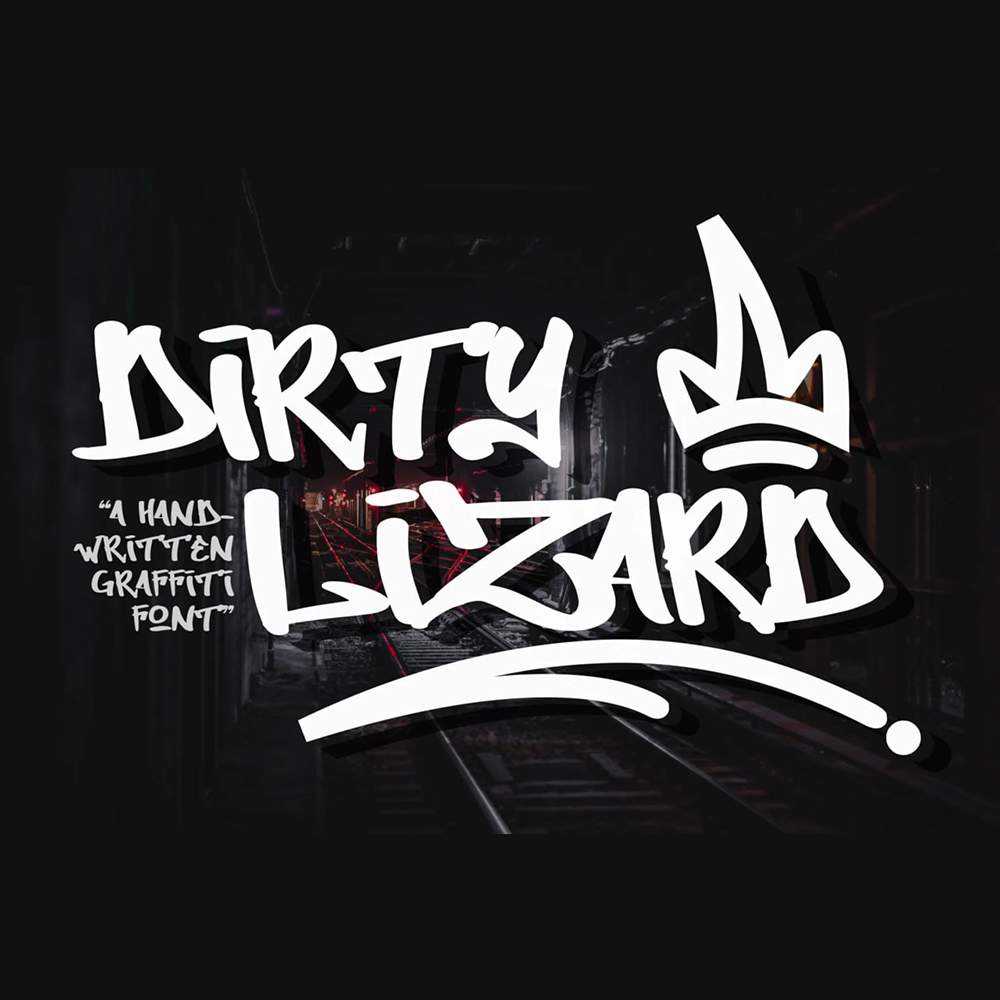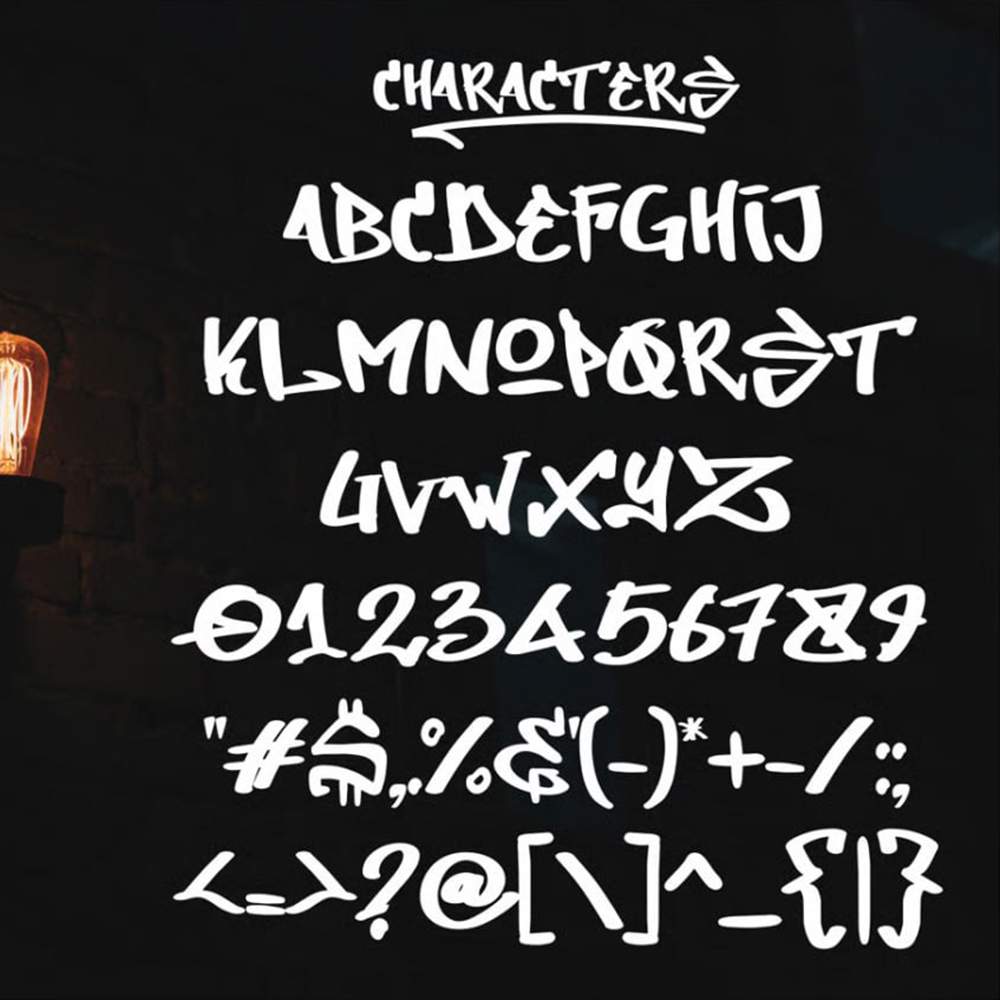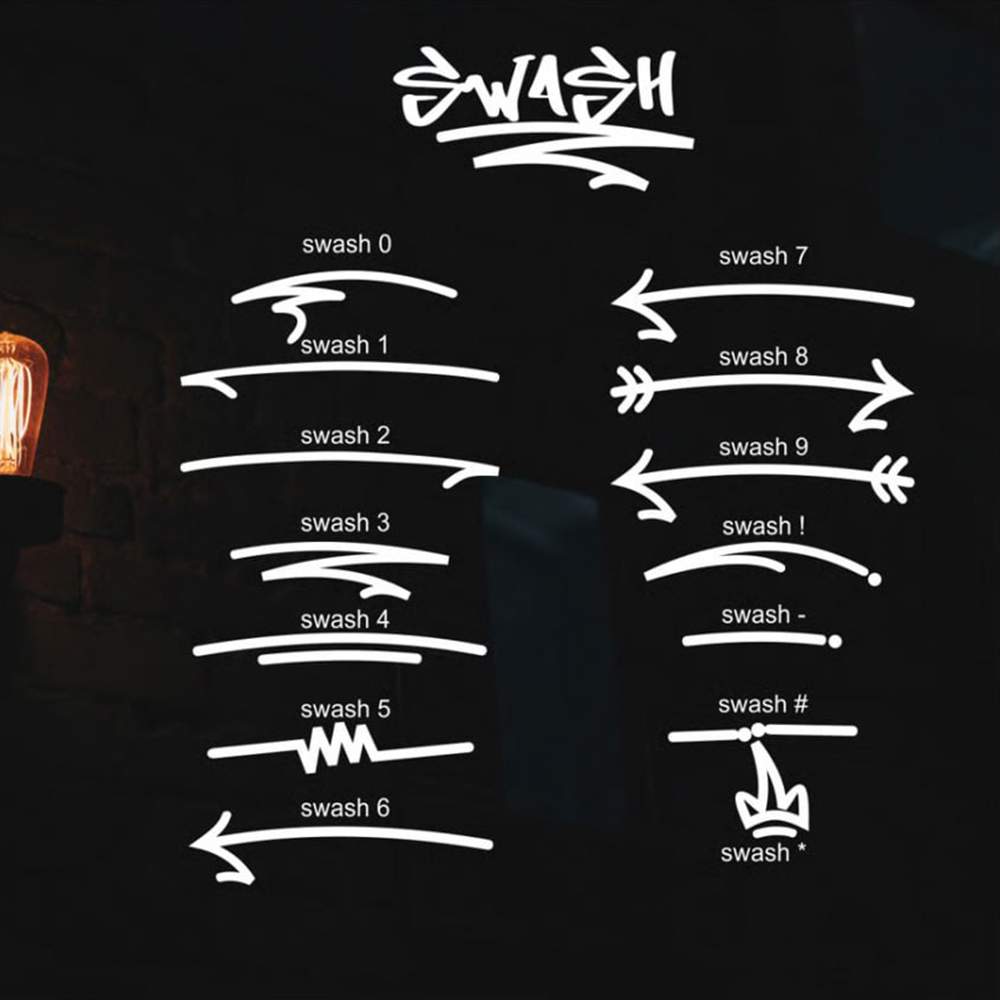
فونت پرمیوم و انگلیسی Dirty Lizard Font یک فونت گرافیتی است که از حروف کوچک پشتیبانی نمیکند و خوانایی بالایی ندارد و حس هیجان را منتقل میکند.…
فونت پرمیوم و انگلیسی Dirty Lizard Font یک فونت گرافیتی است که از حروف کوچک پشتیبانی نمیکند و خوانایی بالایی ندارد و حس هیجان را منتقل میکند. استفاده از فونت Dirty Lizard راهی عالی برای ارتباط با مخاطبان جوان و جذب آنها با محتوای گرافیکی مانند پوستر، لوگو و بروشور است.
مزایای استفاده از فونت لاتین Dirty Lizard چیست؟